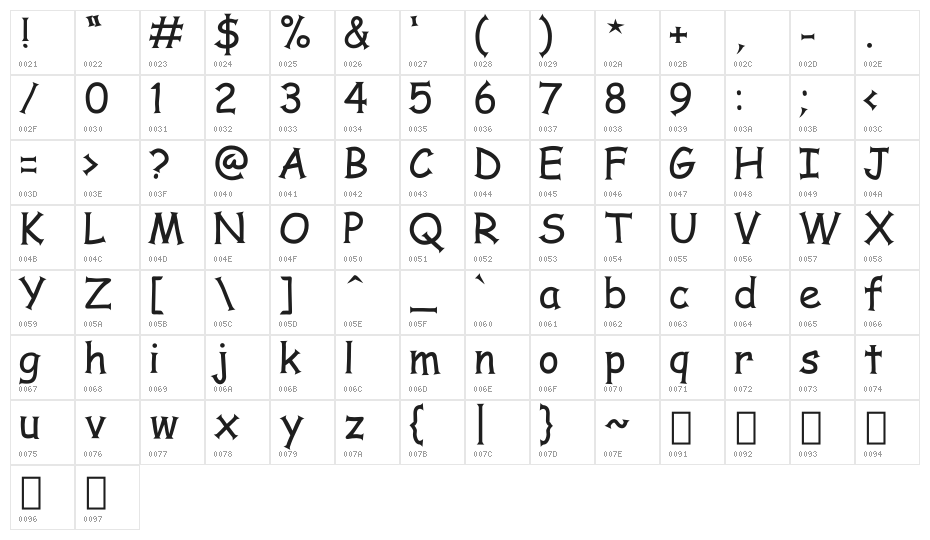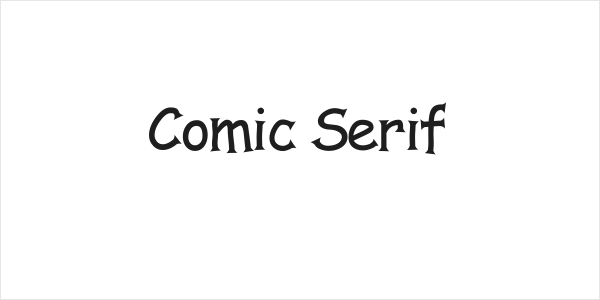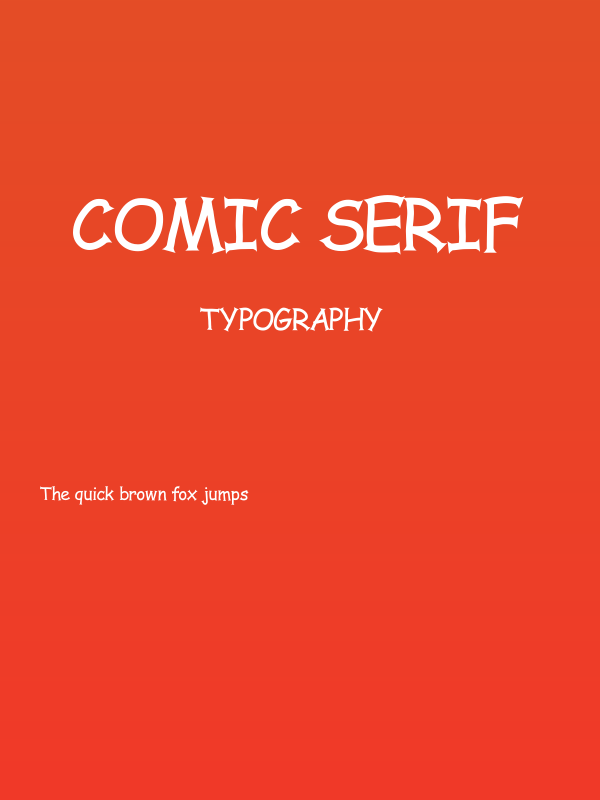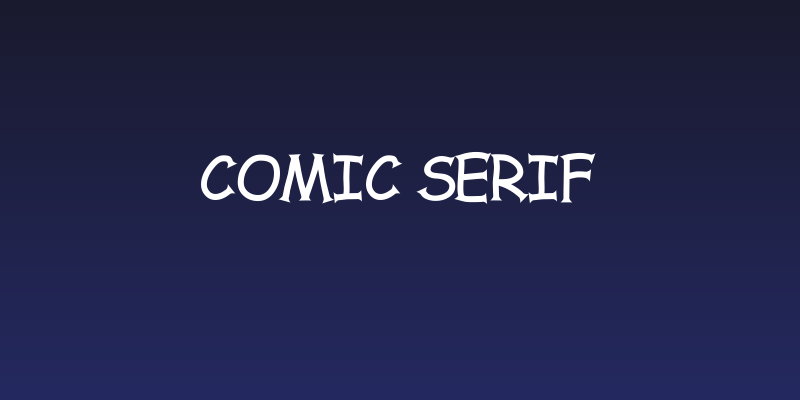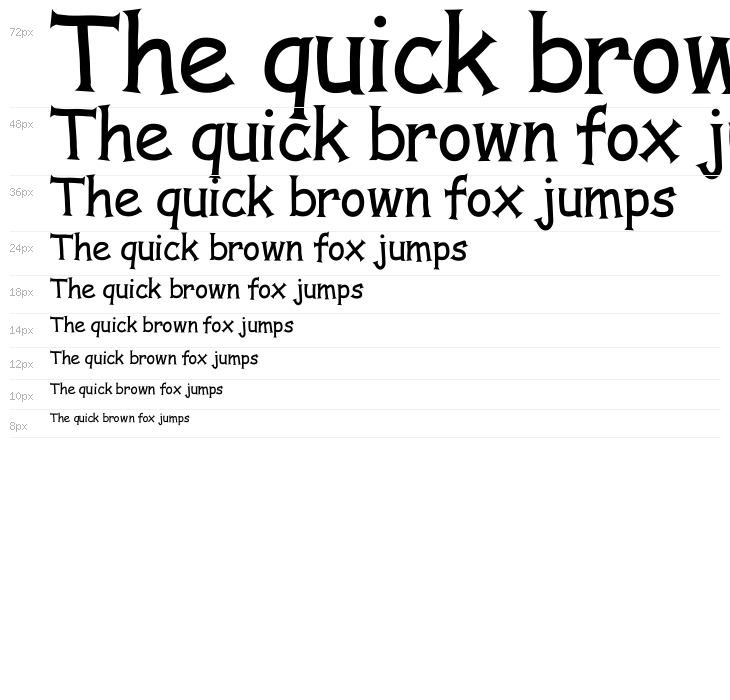
Comic Serif Font
| Stile generale | Playful, Whimsical |
| Caso d'uso | Headlines, Logos, Informal Text |
| Progetti proposti | Ideal for children's books, comic strips, playful branding, and informal invitations. |